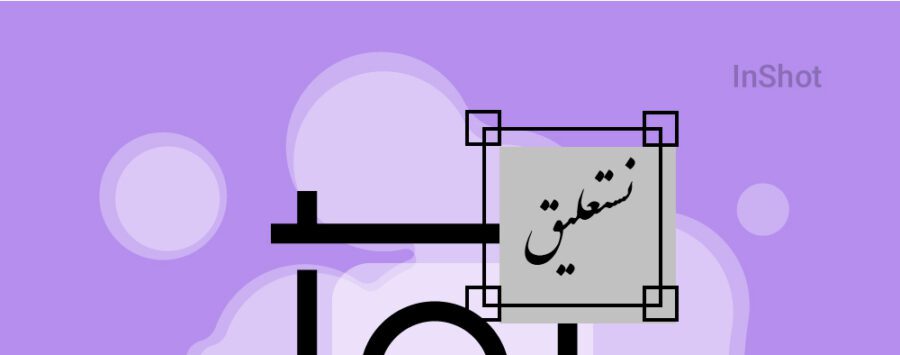
فونت نستعلیق برای اینشات یکی از جذابترین فونتهایی است که میتواند ویدیو و تصاویر شما را در رسانههای اجتماعی، جذاب و منحصربهفرد کند! به طور معمول در اینستاگرام فونتهای پیش فرضی وجود دارند که البته خیلی محدود هستند. در حالی که فونت نستعلیق فوقالعاده متفاوتتر و خاصتر از فوقنتهای عادی است و مخاطب را به راحتی جذب میکند.
بنابراین شما میتوانید این فونت را در برنامه اینشات خود قرار داده و روی عکسها و ویدیوها تبلیغاتی بگذارید. سپس با قرار دادن این موارد درون صفحههای خود در رسانههای اجتماعی، ویو بیشتری دریافت کنید و درآمد خود را افزایش دهید. در این مقاله نحوه نصب و اضافه کردن فونت نستعلیق برای برنامه اینشات را برای شما توضیح میدهیم.
انواع فونت نستعلیق در اینشات
برای اضافه کردن فونت نستعلیق، ابتدا باید مراحل خاصی را طی کنید. این فونت در حالت عادی در برنامه اینشات وجود ندارد. بنابراین زمانی که وارد این برنامه در گوشی میشوید، تنها میتوانید به چند فونت انگلیسی ساده دسترسی پیدا کنید! البته فونتهای انگلیسی اینشات برای زبان فارسی مناسب نیست و زیبای بصری خاصی ندارد. از این رو بهتر است با انواع فونت نستعلیق در اینشات آشنا شوید تا برای جذب مخاطب و افزایش بازدید ویدیو و تصاویر ارسالی، از فونتهای زیر استفاده نمایید:
- دیما نستعلیق (Dima Nastaligh)
- دیما شکسته(Dima Shekasteh)
- ایران نستعلیق(IranNastaliq)
- شکسته(Shekasteh V2.001)
8. اکنون صفحهای برای شما باز میشود که در واقع همان فایلهای گوشی است و شما باید در پوشهای که قبلا فونت نستعلیق را در آن قرار دادید، فونت را انتخاب کنید.
9. زمانی که این فونت را انتخاب کردید، کار شما تمام میشود و فونت خیلی سریع به برنامه اینشات انتقال پیدا میکند.
10. بعد از این مرحله، فونت برای همیشه در اینشات شما باقی میماند. پس هر زمانی که خواستید، میتوانید از آن استفاده کنید. تنها کافی است که بعد از این که متنی را نوشتید، روی گزینه Aa بزنید و فونت آن را روی نستعلیق قرار دهید.
فونت نستعلیق، یکی از زیباترین فونتهای اینشات
استفاده از فونت نستعلیق اخیرا رواج بسیار زیادی داشته است. این فونت به خاطر این که حس و حال شاعرانهای دارد، برای متن و فیلمهای هنری فوقالعاده جذاب است و میتواند یک گزینه بسیار مناسب برای افزایش ویو و لایک شما در رسانههای اجتماعی باشد. به این ترتیب اگر شما هم یک تولیدکننده محتوا حرفهای فارسی هستید، فونتهای تکراری را کنار بگذارید و از فونتهای جدیدی مانند نستعلیق استفاده کنید! همچنین این فونت برای نوشتن جملات انگلیسی، انتخابی بسیار جذاب و منحصربهفرد است. اگر فقط یک بار از آن استفاده کنید، متوجه تاثیر فوقالعاده آن میشوید و برای اینکه دوباره از نتایج آن لذت ببرید، ویدیوها و تصاویر خود را با این فونت تغییر میدهید.
سخن پایانی
در این مطلب نحوه اضافه کردن فونت نستعلیق برای اینشات را برای شما توضیح دادیم و گفتیم که چگونه میتوانید در کوتاهترین زمان ممکن، متنهایی با فونت نستعلیق بسازید! این فونت جذابیتهای زیادی دارد و میتواند یکی از بهترین گزینهها برای نوشتههای فارسی باشد. به این ترتیب، بهتر است آن را به برنامه اینشات خود اضافه کنید و برای تولید محتوای خود به رساغ این فونت شاعرانه فارسی بروید. اگر هر سوال دیگری درباره نحوه اضافه کردن سایر فونتها و یا اضافه کردن همین فونت به برنامه اینشات دارید در قسمت نظرات سوالات خود را از ما بپرسید.
فونت نستعلیق برای اینشات [ آموزش تصویری و گام به گام]